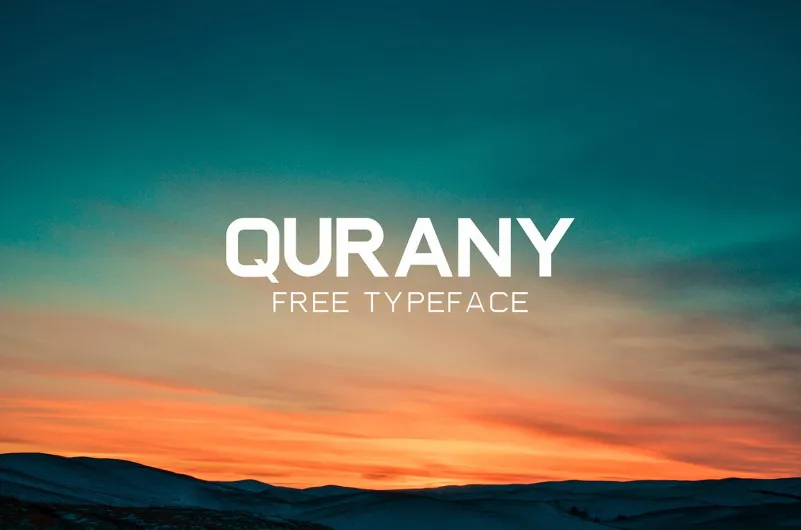
Qurany Font Family – Download Grátis
A “Qurany Font Family” é uma valente família de fontes serifa sem serif que oferece uma grande variedade para atender a uma ampla gama de usos. Ela inclui quatro fontes com dois pesos – bold e light, além das versões regular e itálica. Essa família de fontes abrange letras maiúsculas, números e pontuação, adequada tanto para logotipos e cabeçalhos quanto para banners, posters, revistas, impressões e muito mais. Repleta de elegância e robustez, essa familia de fontes não apenas oferece uma experiência visual atraente em diversas aplicações gráficas, mas também se destaca como uma excelente opção para estilos modernos ou futuristas que valorizam simplicidade e clareza. Englobando os requisitos do design de logo, headlines até impressões digitais, ela é um recurso confiável e versátil para aqueles buscando uma fonte sem serif vibrante e robusta.